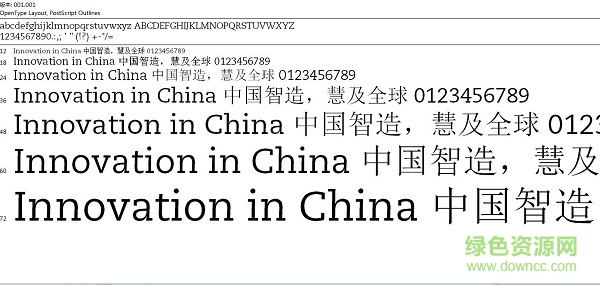
caecilia字體是一款適合用于編程設(shè)計(jì)或是網(wǎng)頁(yè)設(shè)計(jì)的電腦英文字體,結(jié)構(gòu)均勻,干凈優(yōu)美,整潔易讀,視覺觀看非常舒服,具有極佳的實(shí)用性,需要的朋友快來綠色資源網(wǎng)免費(fèi)下載吧!
1.灰度關(guān)系是指單字結(jié)體構(gòu)成和群字組合的關(guān)系。群字組合形成黑白均勻適中,灰度一致,印刷中的字毯灰度關(guān)系。
2.單字結(jié)體構(gòu)成中的灰度關(guān)系是指設(shè)計(jì)單個(gè)字中的筆畫之間的空間所產(chǎn)生的黑白均勻關(guān)系。
3.設(shè)計(jì)活字時(shí),字毯灰度要求每個(gè)字的灰度傾向一致性,在筆畫粗細(xì)上,也尋求視覺上的均勻,使之產(chǎn)生一致的感覺